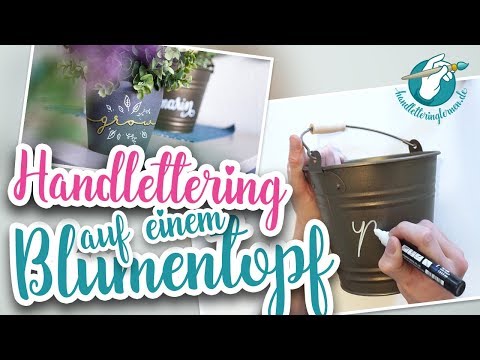
Einen Blumentopf beschriften – Tolle Deko und Geschenkidee
Pflanzen sind eine fantastische Dekoration und verbessern das Raumklima. Außerdem sind sie ein beliebtes Geschenk zu allen möglichen Anlässen.
Doch es geht (natürlich) noch schöner: Einfach selbst einen Blumentopf beschriften! Mit ein paar einfachen Handletterings wird aus jedem einfach Blumentopf ein tolles, individuelles Geschenk. Oder ein charmantes Deko-Objekt für Garten und Fensterbank.
Der passende Blumentopf
Als ich neulich einen tollen Blumentopf, in Form eines Metall-Eimers, in einem Pflanzengeschäft entdeckt habt, war sofort klar, dass der Topf beschriftet werden muss!
Die dunkle, leicht kupferfarbene Oberfläche schreit geradezu nach einem weißen Schriftzug. Und da ich schon wusste, welche Pflanze später in dem Blumentopf stehen würde, habe ich direkt losgeschrieben.
Du kannst natürlich jeden Blumentopf bemalen oder beschriften. Es gibt keine Grenzen! Auf dunklen Töpfen machen sich helle Farben natürlich besonders gut, da ein toller Kontrast entsteht. Auf meinem Topf hätte auch ein Gold-Stift fantastisch ausgesehen.
Ran an die Stifte
Nach ein paar Vorzeichnungen mit dem Bleistift, um den passenden Stil zu finden und ein Gefühl für die Wortlänge zu bekommen, ging es los. Ich habe dazu meinen weißen Lackmarker von POSCA genommen und mich der Faux Calligraphy bedient.
Für die Beschriftung solltest du auf jeden Fall ebenfalls einen Lackmarker benutzen. Die Stifte decken besonders gut und sind nach dem Trockenen auch meist wetterfest. Du kannst deinen beschrifteten Blumentopf also sogar in den Garten oder auf die Terrasse stellen.
Blumentopf beschriftet
Und schon entsteht ein tolles Gesamt-Kunstwerk aus Blumentopf, Pflanze und einem einfachen Lettering. Klasse, oder?
Natürlich blieb es nicht bei einem einzelnen Blumentopf. Ganz schnell folgten noch weitere, selbst bemalte Töpfe mit unterschiedlichen Schriftzügen:
Zweiter Blumentopf